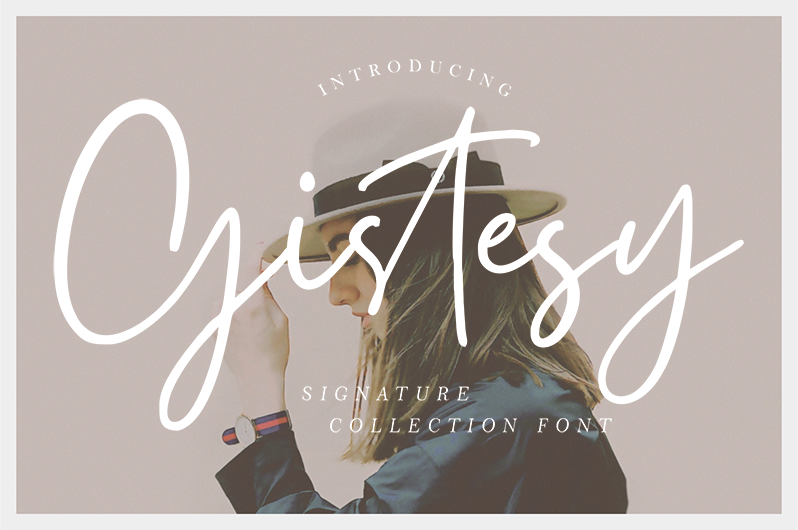
GISTESY هو الخط المثالي لجميع تصميماتك الممتعة. الخط الفرعي هو SIGNATURE.
قد يختلف مظهر الخط GISTESY بناءً على الحروف المحددة. قد لا تدعم بعض الخطوط الأحرف الخاصة أو قد تم تصميمها لأغراض محددة. يوضح التمثيل المرئي أدناه تصميمات الأحرف الفردية. بالإضافة إلى ذلك، لديك خيار معاينة طباعة جميع الحروف أو تجربة اختبار عبر الإنترنت قبل تنزيل الخط.